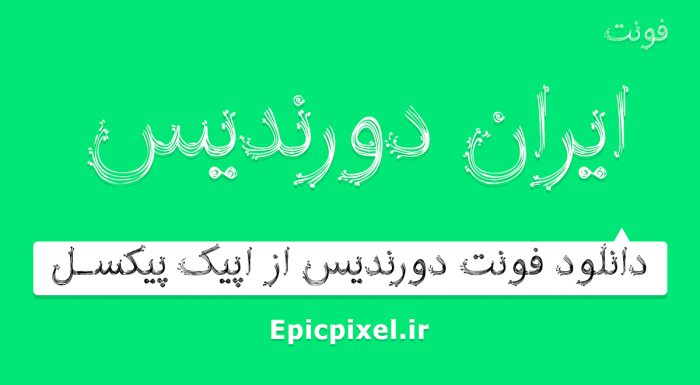
فونت ایران درندیس فارسی
فونت ایران درندیس
چرا فونت ایران درندیس را بشناسید؟
فونت ها چشم های حروف هستند. هر حرف با فونت مختلفی یک شخصیت مختلف دارد و یک پیام مختلف منتقل می کند. فونت ها تأثیر بسزایی بر روی زیبایی، خوانایی و ارتباط متن با مخاطب دارند. برای همین، انتخاب فونت مناسب برای هر پروژه گرافیکی یک مهارت ضروری است.
اما چگونه می توان فونت مناسب را انتخاب کرد؟ چه فونت هایی برای چه کاربردهایی مناسب هستند؟ چه فونت هایی در دسترس هستند و چگونه می توان از آن ها استفاده کرد؟
در این مقاله، قصد داریم به شما یک فونت خاص و جذاب را معرفی کنیم که شاید تا به حال با آن آشنا نبوده باشید. این فونت، فونت ایران درندیس نام دارد و یک فونت گرافیکی و تزئینی است که توسط سنا درندیس طراحی و اجرا شده است. این فونت بر اساس قلم ایران معمولی ساخته شده است ولی با الهام از گل و گیاه شکلگیری کرده است.
فونت ایران درندیس یک فونت منحصر به فرد و خلاقانه است که می تواند به شما در خلق پروژه های گرافیکی جذاب و جالب کمک کند. اگر شما هم علاقه مند به آشنایی با این فونت هستید، با ما همراه باشید.
فونت ایران درندیس چگونه ساخته شده است؟
فونت ایران درندیس یک نسخه تزپینی گیاهی از قلم ایران معمولی است که توسط سنا درندیس طراحی و اجرا شده است. این طراحی با قلم روی کاغذ اجرا شده است و سپس به صورت مستقیم به فونت تبدیل شده است. برای درک بهتر روش طراحی و تولید فونت ایران درندیس، لازم است که با طراح فونت، قلم ایران و الگوراتم تزئین قلم آشنا شویم.
قلم ایران: الگو و الهام
قلم ایران معمولی یک قلم فارسی است که توسط مصطفی عباسزاده طراحی شده است. این قلم بر پایه قلم نستعلیق ساخته شده است ولی با حذف بخش های زائد و با رعایت تعادل بین خط های صاف و منحنی، چشم نوازتر و خواناتر شده است. قلم ایران معمولی دارای ۴ وزن (روشن، معمولی، سنگین و بولد) است و مناسب برای متن های رسمی، علمی، آموزشی و … است.
گل و گياه: تزئين و خلاقيت
برای طراحي فونت ايران درنديس، سنا درنديس از يك الگوريتم تزئيني استفاده كرده است كه بر پايه الگوبرداري از گل و گياه مي باشد. اين الگوريتم شامل دو مرحله است:
مرحله اول: در اين مرحله، حروف قلم ايران معمولي را با قلم روي كاغذ نوشته و سپس با كاربرد خطوط منحني و نقطه گذاري، حروف را با شكل هاي گياهي تزئين مي كند. اين شكل ها ممكن است از برگ، گل، ساقه، شاخه و … باشند.
با استفاده از اين الگوريتم، سنا درنديس توانسته است يك فونت خلاقانه و زيبا را خلق كند كه هم با قلم ايران همخواني دارد و هم با گل و گياه رابطه دارد.
فونت ایران درندیس چه ویژگیهایی دارد؟
فونت ایران درندیس علاوه بر زیبایی و خلاقیت، دارای برخی ویژگیهای فنی و زیباییشناسی است که میتواند برای انتخاب و استفاده از آن مفید باشد. در این بخش، به بررسی این ویژگیها میپردازیم.
وزن و اندازه فونت
حروف، علائم و نمادهای فونت
فونت ایران درندیس شامل ۳۲ حرف، علامت و نماد است که به شرح زیر هستند:
حروف الفبای فارسی: ۳۲ حرف
علائم نگارش: نقطه، ویرگول، سؤال، تعجب، نقطهچین
علائم رياضي: جمع، تفريق، ضرب، تقسيم
علائم پول: ريال، دلار، یورو
نمادها: دل، ستاره، گل
فونت ایران درندیس از برخی حروف و علائم پشتیبانی نمیکند. برای مثال، این فونت از حروف عربی مانند ث، ص، ض و … پشتیبانی نمیکند. همچنین، این فونت از علائم مانند کاما، نقطهویرگول، دونقطه و … پشتیبانی نمیکند. برای استفاده از این حروف و علائم، توصیه میشود که از فونتهای دیگر استفاده کنید.
فونت ایران درندیس چگونه استفاده میشود؟
فونت ایران درندیس یک فونت گرافیکی و تزئینی است که میتواند برای ایجاد پروژههای گرافیکی جذاب و جالب استفاده شود. این فونت با الهام از گل و گیاه، قلم را با شکل های گیاهی تزئین کرده است و به متن یک حالت طبیعی و زنده میدهد. در این بخش، به برخی از کاربردها و نمونهکارهای فونت ایران درندیس میپردازیم.
پروژههای گرافیکی با فونت ایران درندیس
فونت ایران درندیس مناسب برای پروژههای گرافیکی مانند پوستر، جلد کتاب، بیلبورد و … است که نیاز به یک تایپوگرافی خلاقانه و منحصر به فرد دارند. این فونت میتواند با رنگ ها، تصاویر و عناصر گرافیکی دیگر ترکیب شود و یک پروژه گرافیکی زیبا و جذاب را خلق کند. برای مثال، میتوانید نمونه های زیر را ببینید:
پوستر با فونت ایران درندیس
جلد کتاب با فونت ایران درندیس
بیلبورد با فونت ایران درندیس
طراحی لوگو با فونت ایران درندیس
فونت ایران درندیس همچنین میتواند برای طراحی لوگو با استفاده از حروف تزئین شده استفاده شود. این فونت میتواند به لوگو یک شخصیت خاص و متمایز بدهد و با رعایت تعادل بین سادگی و زینت، یک لوگو قابل حفظ و شناسایی را خلق کند. برای مثال، میتوانید نمونه های زیر را ببینید: